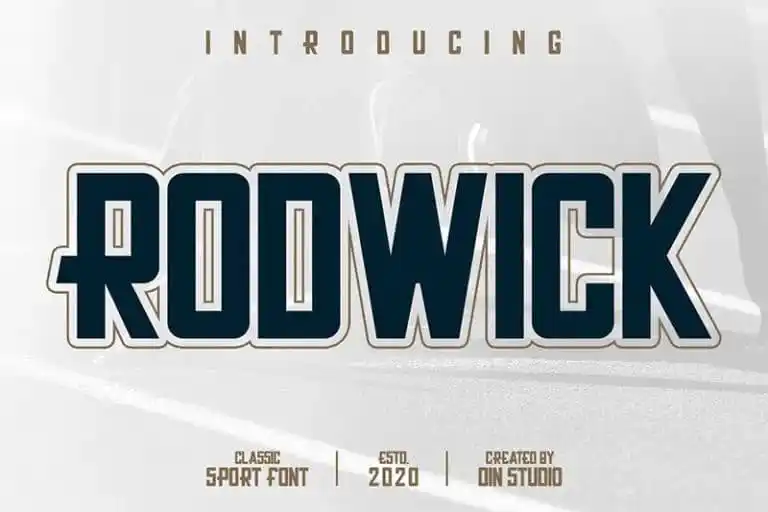
Rodwick Display Font – Fonte Grátis
Rodwick Display Font
A Rodwick Display Font é uma tipografia para desportos que traz a essência do esporte no seu design tradicionalmente clássico. Ideal para projetos profissionais, especialmente aqueles relacionados ao desporto, esta fonte foi criada pensando em seus futuros lançamentos. É perfeita para identidade visual de marca, designs editoriais e de materiais de escritório, design esportivo, moda, jogos, blog, design de publicidade moderna, cartas de convite, citações artísticas, decoração de lar, capítulos/capas de livros ou qualquer evento especial. Seja para um novo projeto editorial em estilo vintage ou uma campanha de marketing esportiva com um toque contemporâneo, a Rodwick Display Font está aqui para capturar o espírito do desporto em sua mais pura forma.